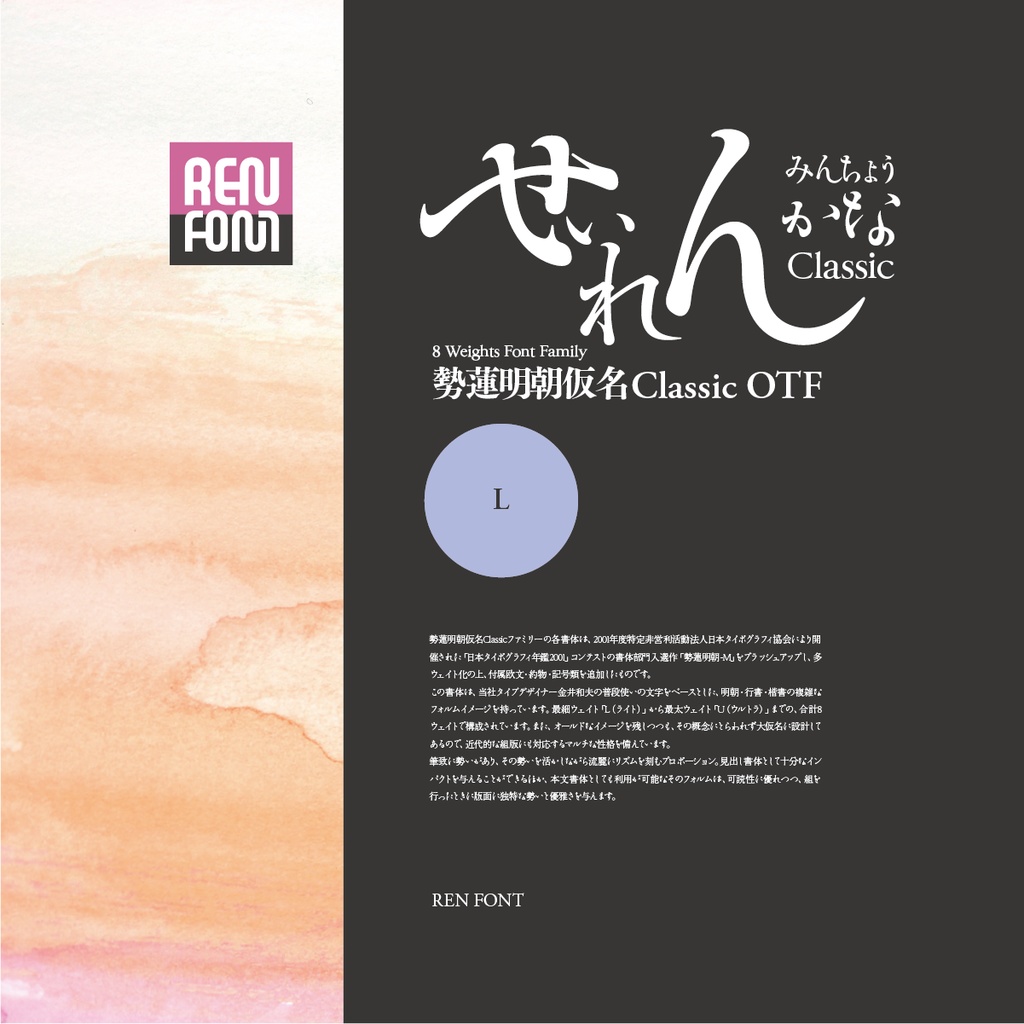
●可読性に優れ勢いと優雅さを兼ね備えた 勢蓮明朝仮名Classic 8ウェイトファミリー / OpenType
相反する、勢いと優美さを融合した手書き風かな明朝。
勢蓮明朝仮名Classicファミリーの各書体は、2001年度特定非営利活動法人日本タイポグラフィ協会により開催された「日本タイポグラフィ年鑑2001」コンテストの書体部門入選作「勢蓮明朝-M」をブラッシュアップし、多ウェイト化の上、付属欧文・約物・記号類を追加したものです。 この書体は、当社タイプデザイナー金井和夫の普段使いの文字をベースとした、明朝・行書・楷書の複雑なフォルムイメージを持っています。最細ウェイト「L(ライト)」から最太ウェイト「U(ウルトラ)」までの、合計8ウェイトで構成されています。また、オールドなイメージを残しつつも、その概念にとらわれず大仮名に設計してあるので、近代的な組版にも対応するマルチな性格を備えています。 筆致に勢いがあり、その勢いを活かしながら流麗にリズムを刻むプロポーション。見出し書体として十分なインパクトを与えることができるほか、本文書体としても利用が可能なそのフォルムは、可読性に優れつつ、組を行ったときに版面に独特な勢いと優雅さを与えます。